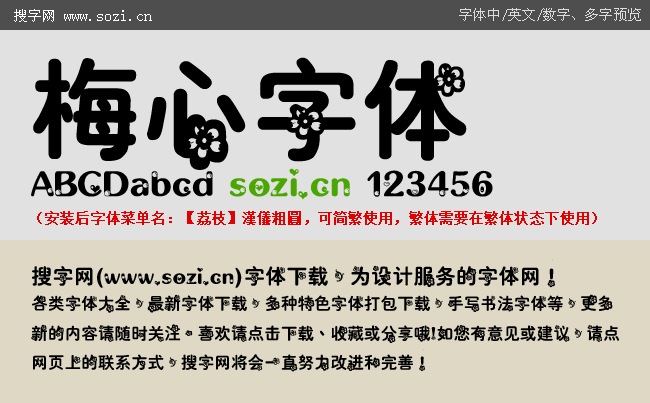
梅心字體
搜字網(wǎng)給大家提供一款梅心字體手機(jī)中文字體下載。這款手機(jī)字體是以圓體字體為原形,筆畫間嵌入了梅花圖案。在具備粗圓字體清晰醒目風(fēng)格的同時(shí),卡通味也特別濃,是一款非?蓯鄣目ㄍㄗ煮w,特別適合喜歡手機(jī)字體個(gè)性一些的朋友在手機(jī)上安裝使用。